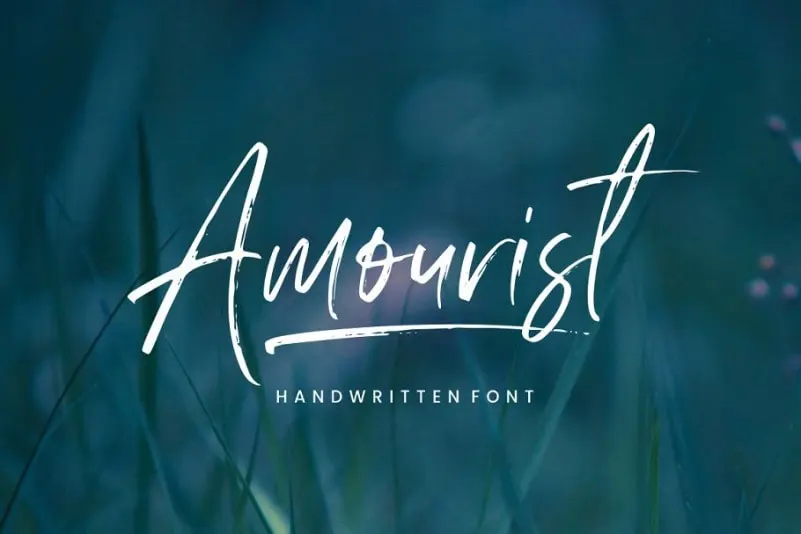
Amourist Handwritten Font – Download Grátis
Amourist Handwritten Font é uma elegante nova adição à gama de fonts escritas a mão disponíveis para designers digitais. Embora apresente um estilo moderno e sofisticado, o design de Amourist remete ao charme romântico da calligrafia manual tradicional. Ideal tanto para aplicativos como logotipos, cartões de convite, papéis de papelaria e até mesmo postagens de redes sociais, Amourist oferece uma fonte perfeita que se adapta a diversos usos. Com suas letras maiúsculas e minúsculas completas, símbolos multilíngues e números, além de pontuação, esta fonte é sua primeira escolha para qualquer projeto. E o melhor? Amourist está disponível em toda a gama de plataformas, sejam eles Android ou iOS, garantindo uma experiência visual impecável em todos os dispositivos que você use. Ao adquirir Amourist Handwritten Font, estabeleça um toque especial e único em seus projetos. Este é o gráfico perfeito para eventos como casamentos, publicidade, embalagens de produtos, criações fotográficas e até mesmo marcações digitais especiais. Com um design que combina a modernidade com uma tradição elegante, Amourist oferece mais do que apenas uma fonte; ela oferece um estilo único para seus trabalhos.